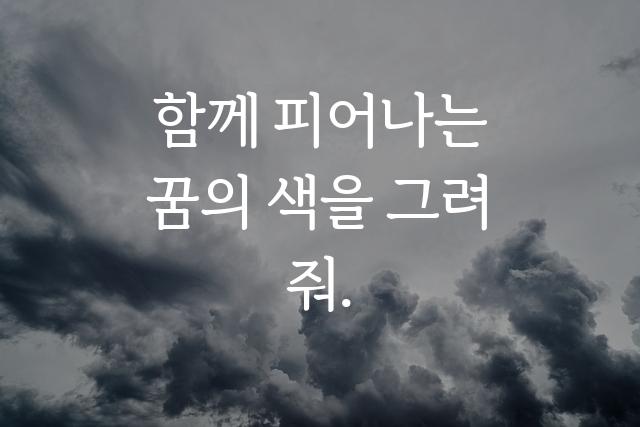
전남교육또박체는 전라남도교육청에서 제작한 기본 고딕 스타일의 폰트로, 깔끔하고 명료한 디자인이 특징입니다. 제목용으로 최적화되어 강한 인상과 시각적 명확성을 제공합니다.
전남교육또박체은(는)
기본 고딕, 감성적인, 부드러움, 길고/크고 계열의 생김새를 가지고 있으며
교육 자료, 어린이 책, 일기/편지 등에서 자주 활용되며, 효과적인 메시지 전달에 적합합니다.
이 폰트는 교육, 유아/가족, 커뮤니티 분야에 잘 어울리며,
친근한, 편안한, 자연스러운 느낌을 담고 있는 것이 특징입니다.
이 폰트와 유사한 폰트로는 나눔바른고딕, 맑은고딕, 굴림 등이 있어요. 함께 비교해 보시면 좋습니다!